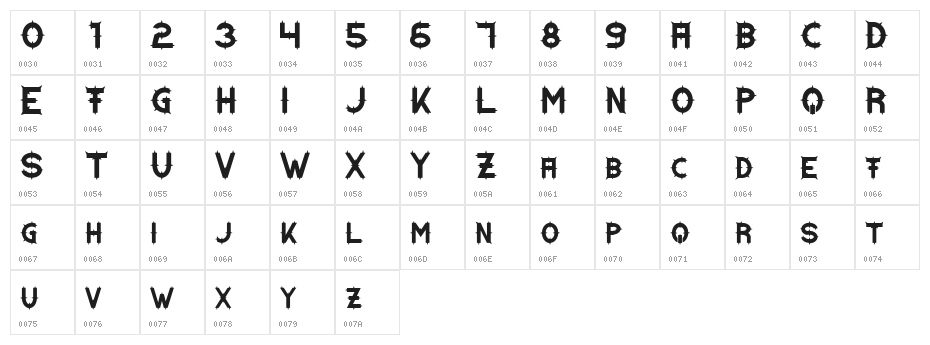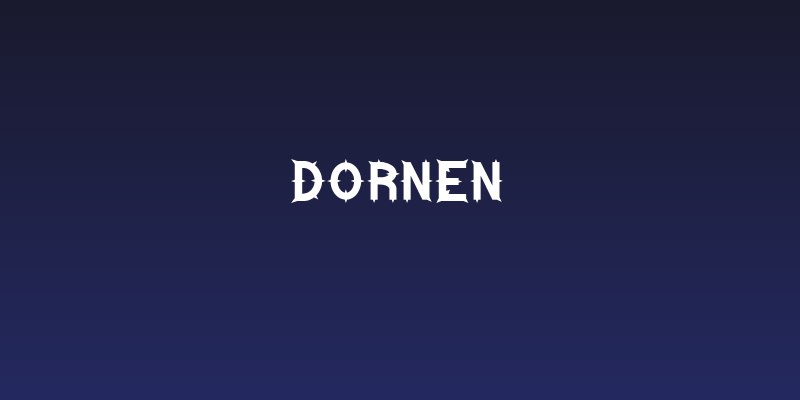
Dornen Font
✎ Gothic
| Categorie | Gothic |
| Stile generale | Gothic, Edgy, Decorative |
| Progetti proposti | Ideal for album covers, horror movie posters, video game titles, or any project needing a dramatic, gothic aesthetic. |